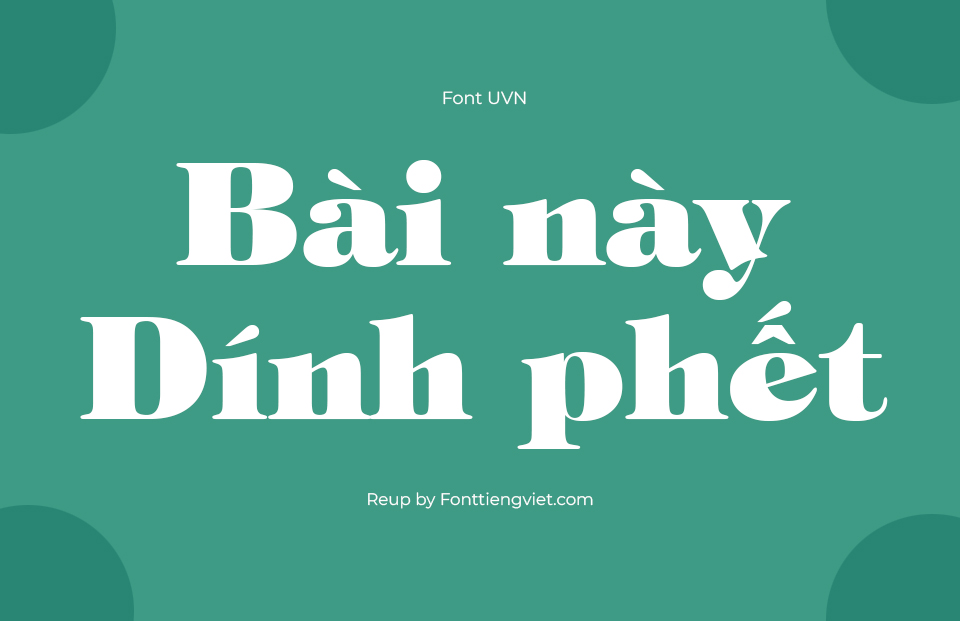
Giới thiệu về Font Việt Hóa UVN Bach Tuyet Nang
Trong thế giới đồ họa dành cho học đường, việc lựa chọn một bộ Font Chữ phù hợp là yếu tố then chốt để tạo nên sự gần gũi và sinh động. Font Việt Hóa UVN Bach Tuyet Nang là một trong những lựa chọn hàng đầu nhờ phong cách nhẹ nhàng, mang đậm tính cổ tích. Bộ font này không chỉ hỗ trợ đầy đủ bảng mã tiếng Việt mà còn giữ được nét thanh thoát, giúp các thầy cô giáo và học sinh dễ dàng trình bày bài giảng hoặc báo tường một cách ấn tượng nhất.
Đặc điểm nổi bật của bộ Font Việt Hóa UVN Bach Tuyet Nang
Thiết kế mềm mại và sáng tạo
Đúng như tên gọi lấy cảm hứng từ nàng Bạch Tuyết, Font Việt Hóa UVN Bach Tuyet Nang sở hữu các đường nét uốn lượn mềm mại nhưng vẫn đảm bảo tính dễ đọc. Đây là một biến thể độc đáo trong dòng UVN, giúp người dùng thoát khỏi sự gò bó của các phông chữ truyền thống. Các ký tự được tinh chỉnh kỹ lưỡng, phù hợp cho cả in ấn lẫn hiển thị trên các thiết bị kỹ thuật số như màn hình máy tính hay máy chiếu.
Tính ứng dụng cao trong học tập
Người dùng thường tìm đến font này khi cần thiết kế bìa sách, nhãn vở hay các ấn phẩm văn hóa trong nhà trường. Nhờ khả năng tương thích tốt với các phần mềm thiết kế như Photoshop, Canva hay bộ công cụ Office, bạn có thể thỏa sức sáng tạo mà không lo lỗi font. Sự hài hòa giữa tính nghệ thuật và kỹ thuật đã giúp bộ font này trở thành công cụ đắc lực cho cộng đồng thiết kế tại Việt Nam.
Kết luận về bộ font chữ độc đáo